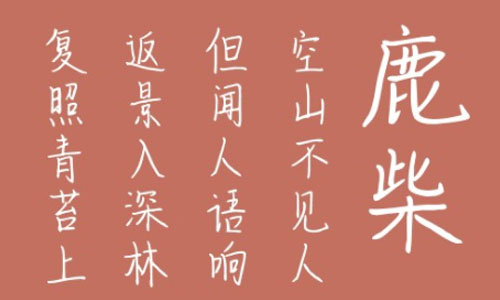
米開(kāi)第一封情書(shū)字體是一款個(gè)性的藝術(shù)手寫(xiě)字體,字體全,書(shū)寫(xiě)清秀,辨識(shí)度好,該字體主要用來(lái)書(shū)寫(xiě)情書(shū),非常的有個(gè)性唯美哦,可以很好的表達(dá)第一次寫(xiě)第一封情書(shū)的意境,歡迎大家前來(lái)下載使用。